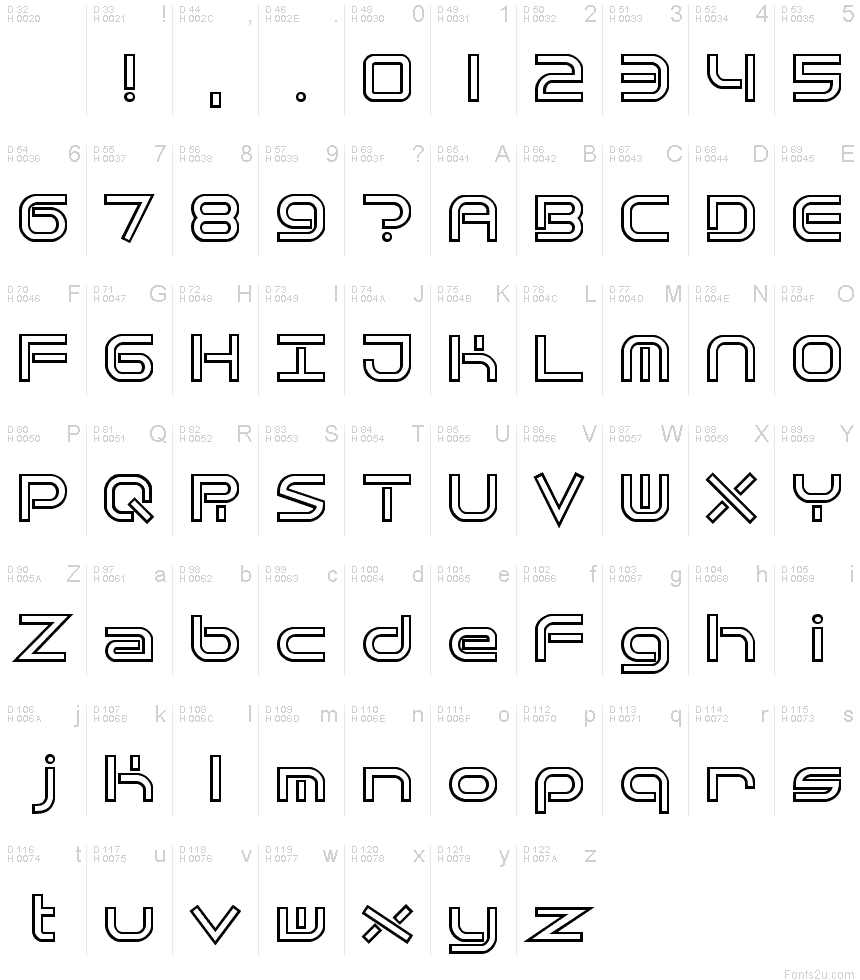
Quantum Flat Hollow od ÆNIGMA Fonts to darmowy, nowoczesny, konturowy krój displayowy z nutą retro-futuryzmu. Litery zbudowane są z gładkich, rurowych pociągnięć o kwadratowych załamaniach i otwartych wnętrzach, co nadaje alfabetowi elegancki, elektroniczny charakter – coś pomiędzy wczesną typografią sci-fi a technologicznym brandingiem końca XX wieku.
Sprawdza się wszędzie tam, gdzie potrzebujesz graficznego tytułu, a nie tekstu do czytania: okładki płyt, plakaty w stylu arcade, grafiki na wydarzenia technologiczne, opakowania czy plansze tytułowe idealnie pasują do tego darmowego fontu. Dzięki temu, że formy pozostają szerokie i lekkie, nawet gdy się przeplatają i wyginają, świetnie nadaje się do krótkich nagłówków, logotypów i monogramów, w których ten pusty, neonowy styl może w pełni wybrzmieć.